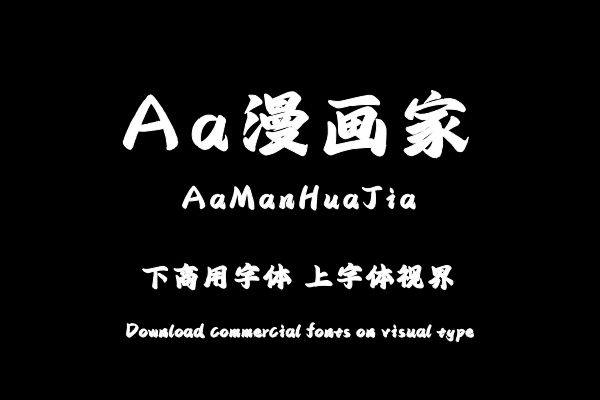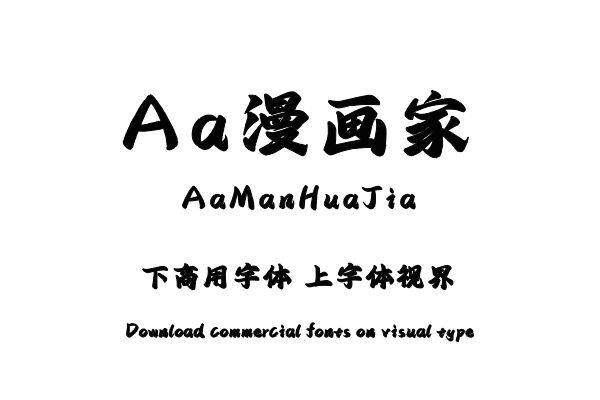
本字体以宽窄两种板刷型笔刷构造全库,构成宽窄对比,笔画衔接松散,断多连少,形成错落不规则的笔画和字形分布,呈现随性可爱的视觉效果。购买须知:“下载服务费”与“字体VIP”所获得字体 仅用于个人非商用, 商用请联系付费授权。本字体为电脑用字,手机没有root权限不支持直接手机换字(手机如何root,请自行百度搜索教程)。购买前请先 了解清楚后再付款 ,字体为虚拟产品无法回收 一旦购买不支持退款。